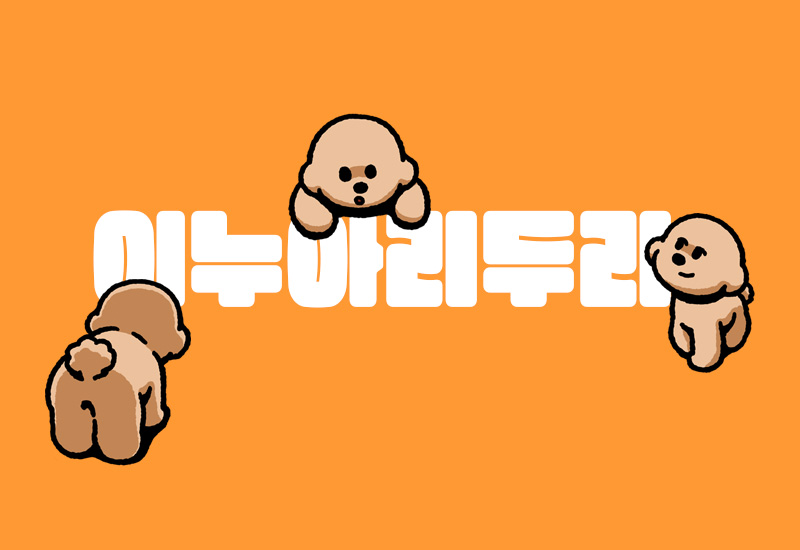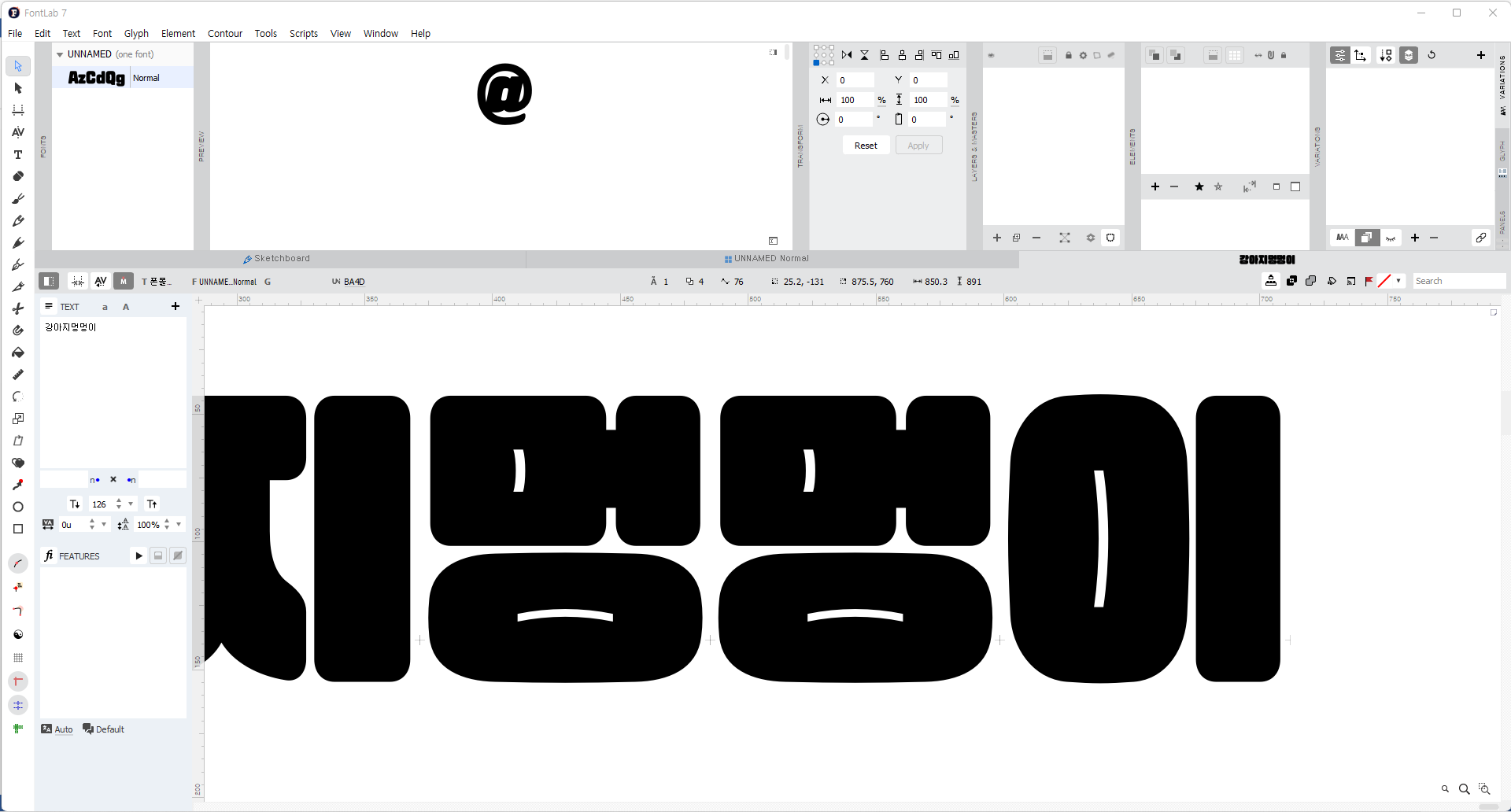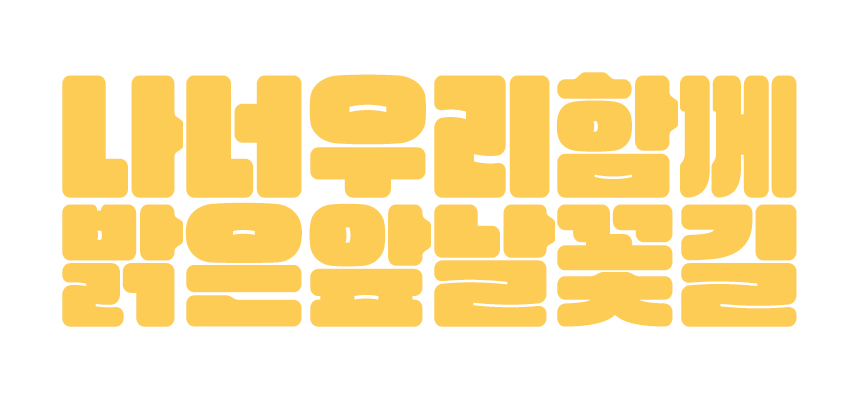
RixFont X 너무 귀여워서 푸들푸들
동글동글 귀여운 생김새, 다양한 표정을 가진 푸들 가족 이누, 아리, 두리를 닮은 서체 「Rix이누아리두리」를 소개합니다. 이번 6월의 신규 폰트는 특별히 인기 인스타툰 <너무 귀여워서 푸들푸들>의 주인공 이누아리두리네와 함께 콜라보로 기획해, 누구나 무료로 사용할 수 있도록 제작한 서체입니다. 폰트를 디자인한 이지윤 디자이너와의 인터뷰를 통해 더 자세히 알아볼게요-!
안녕하세요. 소개 부탁드려요!
안녕하세요! Rix이누아리두리체로 돌아온 폰트 디자이너 이지윤입니다.
따뜻한 6월 출시한 Rix이누아리두리체, 어떻게 제작하게 되셨는지 궁금해요!
서체 작업을 하다 보면 검은 공간이 아닌 글자의 흰 공간을 보라는 말을 자주 듣곤 합니다. 그래서 ‘속공간의 형태에 재미를 주면 어떨까?’라는 생각을 하게 되었고, 마침 이와 관련한 레퍼런스 자료들을 찾게 되었어요. 영문에는 이런 실험적인 디자인이 많더라고요.
또 아래 사진처럼 최소한의 속공간으로도 글자 간에 변별이 이루어지는 걸 보면서 변별에 있어서 글자의 “형태”만큼 “맥락”도 중요하다는 걸 알았어요. 왼쪽 이미지만 보면 무슨 글자인지 알 수 없지만, 전체(오른쪽 이미지)를 놓고 봤을 때는 'F'로 인식하는 것처럼요. 이번 디자인은 다소 실험적인 형태를 가지고 있지만 맥락 안에서 충분히 읽힐 수 있다는 점을 잊지 않고 작업하려 했습니다.
폰트명은 어떻게 탄생하게 되었나요?
처음에는 Rix삐쭉이라는 이름을 지어줬는데, 받침으로 들어가는 자소들의 속공간 형태를 '삐쭉' 우는 입모양의 형태로 만들면서 나온 이름이에요. 물론 웃는 형태도 있지만, '삐쭉'이 입에 잘 붙더라고요 ㅎㅎ 그리고 서체명을 통해서 '표정'을 가진 서체임을 나타내고 싶었습니다. 이게 가장 큰 특징이니까요! 그러다 이누아리두리라는 강아지 인스타그램 계정과 콜라보를 진행하게 되었고, 서체의 느낌과 일러스트가 잘 어울려 서체명을 이누아리두리체로 바꾸게 되었습니다.
Rix이누아리두리체는 이 부분이 특히 매력적이다! 마구 자랑해 주세요.
통통하고 동글동글한 형태를 가지고 있어서 일단 귀엽습니다. 또 자소에 따라 속공간이 변하면서 울고, 웃는 인상을 주는 재미있는 서체예요. 저는 개인적으로 같은 글자가 반복되어 나오는 단어나 문장보다는 다양한 자소가 모여있을 때 더 귀여운 것 같아요.
어디에, 어떻게 사용하면 좋을지?
처음에는 짧은 제목의 책 표지나 포스터 등에 쓰이는 걸 생각하고 제작했어요. 그런데 예능 자막이나 광고 포스터에도 쓰일 수 있겠다는 생각이 들더라고요. 콜라보로 진행되는 무료 서체인 만큼 다양한 곳에서 마구마구 쓰였으면 좋겠습니다.
이번 폰트 디자인을 완성하며 느낀 점!
평소 귀엽고 획이 두꺼운 제목용 서체를 만들어 보고 싶었는데 제작할 수 있게 되어서 좋았습니다. 또 무료 서체인 만큼 다양한 매체에서 많이 보였으면 좋겠네요'◡'
Rix이누아리두리체는 귀여운 반려견 이누, 아리, 두리와의 일상을 그리는 인스타툰 <너무 귀여워서 푸들푸들> 이누아리두리네와의 콜라보로 기획하여 강아지를 사랑하는 모든 사람들을 위해 무료로 배포하는 폰트입니다.
댕댕이들의 반려인으로 살아가는 휴먼에게 너무나 소중한 가족인 친구들! 일상을 함께 살아가면서 마주하게 되는 아이들의 다양한 표정들, 그 안에는 웃음, 슬픔, 신남, 화남 등 다채로운 감정들을 있죠. Rix이누아리두리는 그런 다양한 표정들을 담아낸 귀엽고 재미있는 서체입니다.
이누아리두리체는 네모꼴에 꽉 찬 골격과 두꺼운 획으로 주목도가 높은 제목용 서체입니다. 푸들 친구들의 닮은 동글동글한 형태와 부드러운 굴림이 귀여운 인상을 주고, 글자 속공간에 재미를 주어 다양한 표정을 담은 글꼴입니다.
자소마다 다른 *속공간은 웃는 얼굴이 되기도 하고 우는 얼굴이 되기도 해서 마치 글자에 표정이 있는 것처럼 보입니다. 자소 형태와 위치에 따라 달라지는 속공간을 찾는 재미도 있습니다.
*속공간(Counter)
글자나 기호 속에 들어간 공간, 글자 줄기에 둘러싸인 공간을 말합니다. 한글에서 'ㄷ'은 열린 속공간, 'ㅇ'은 닫힌 속공간이 들어간 글꼴로 볼 수 있습니다. 글자 속공간이 크고 작음으로 해서 글자꼴의 시각적 크기를 결정하는 요인이 되기도 하며, 글자꼴이 주는 이미지에도 영향을 미칩니다.
숫자나 영문, 특수 기호에도 동일한 스타일이 적용되어 함께 쓸 때 자연스럽고 통일감을 줄 수 있어요😉
여러 가지 굿즈에 적용된 모습. 너무 귀엽죠?!🐕 댕댕이, 냥이 관련 디자인에 활용하면 특히 찰떡이고 일러스트나 패턴과 함께하면 귀여움이 배가 되는 폰트입니다.